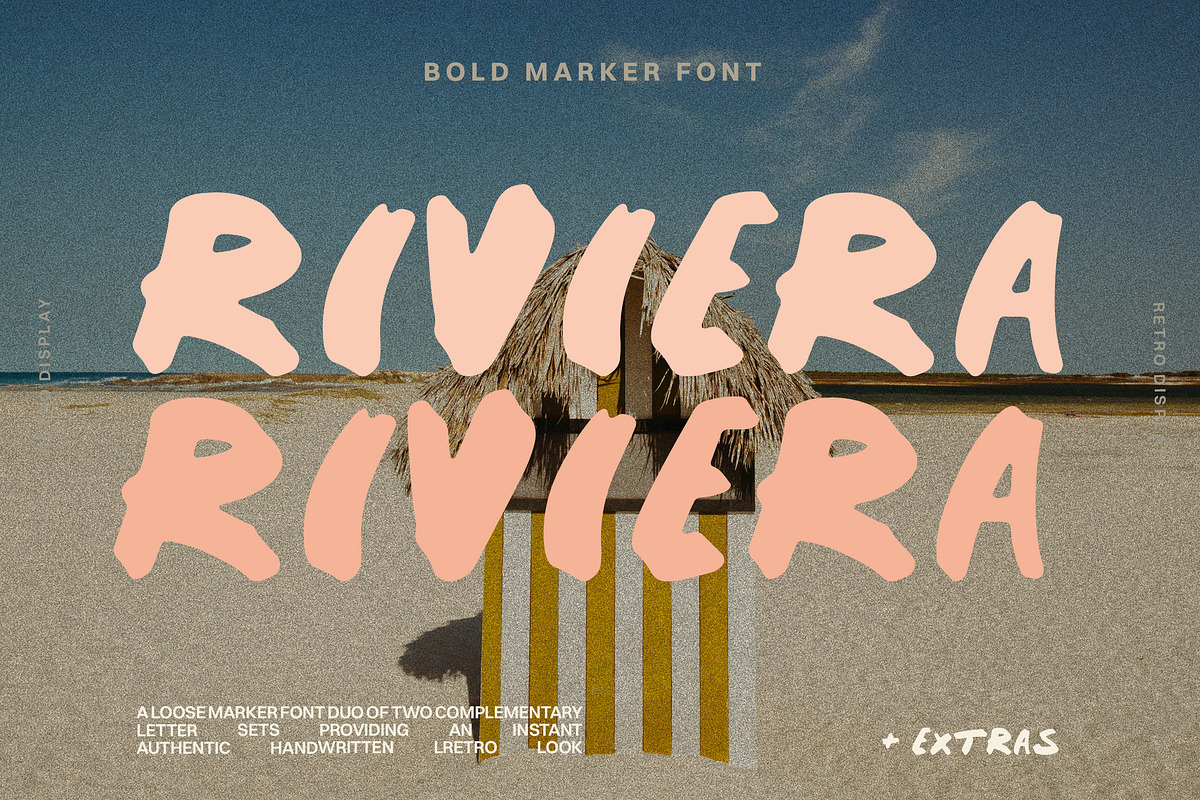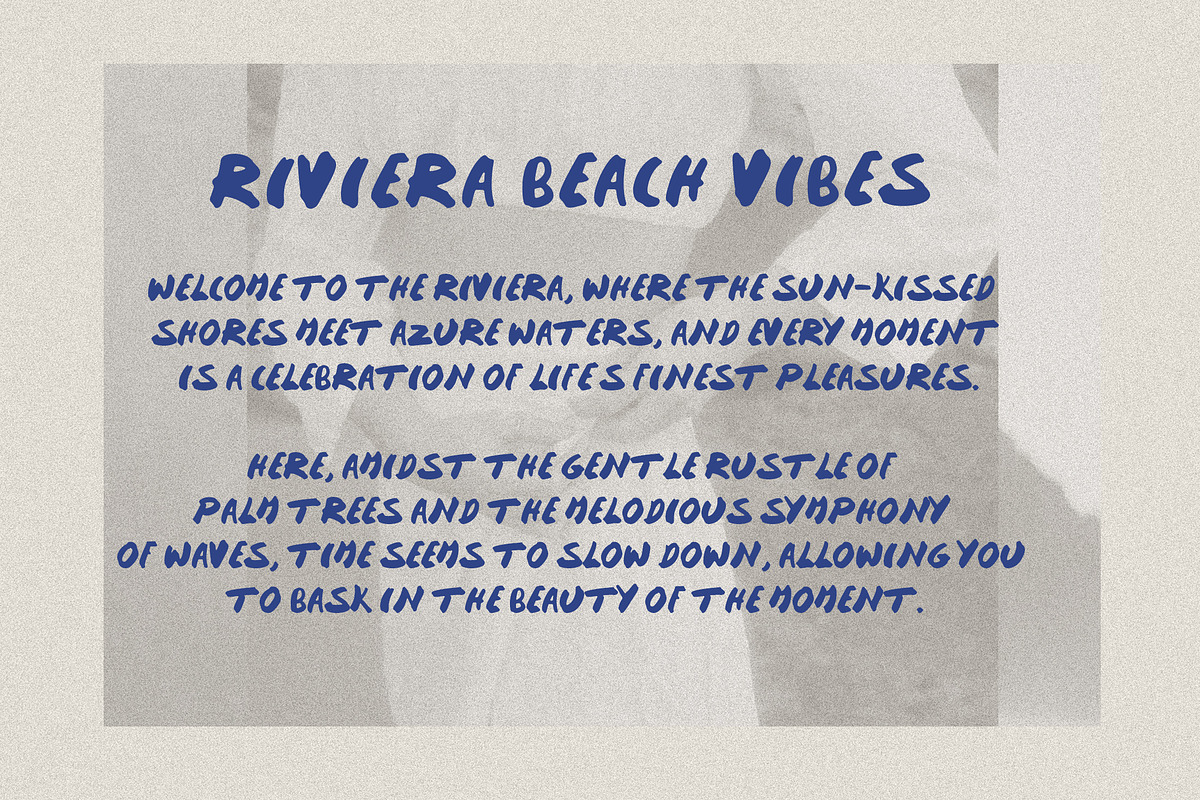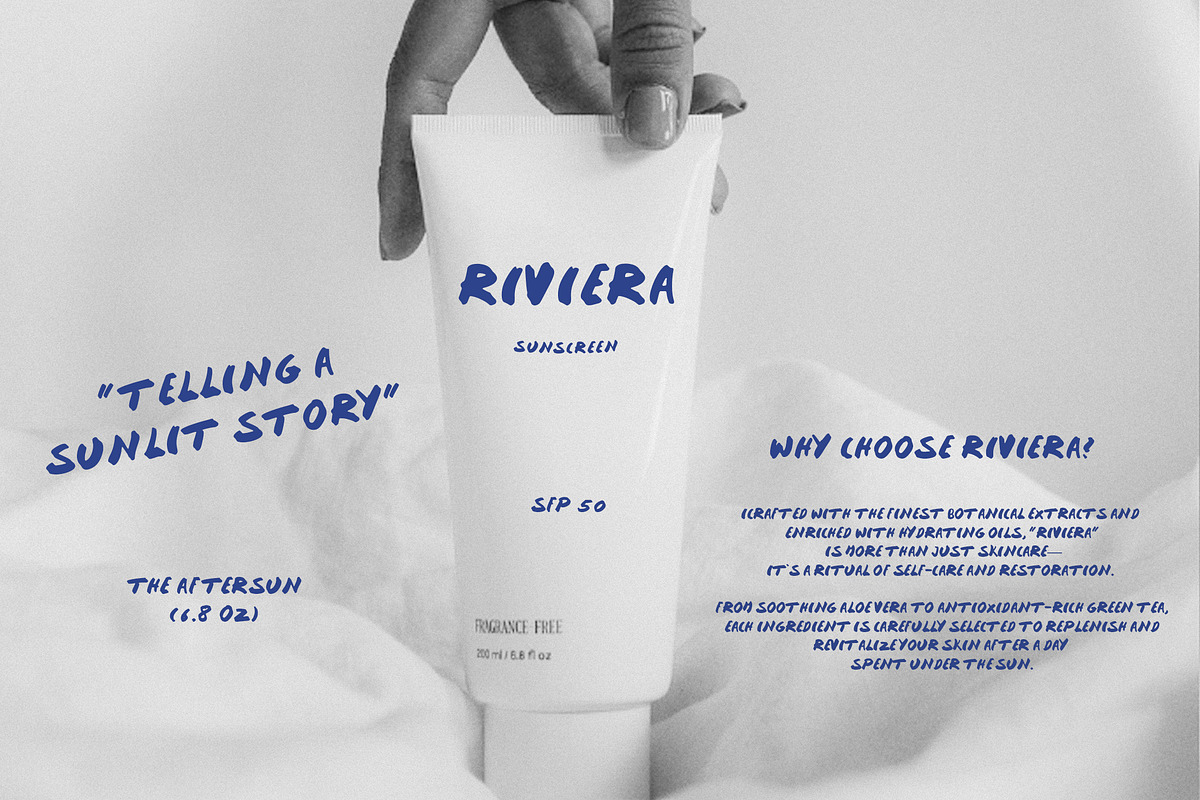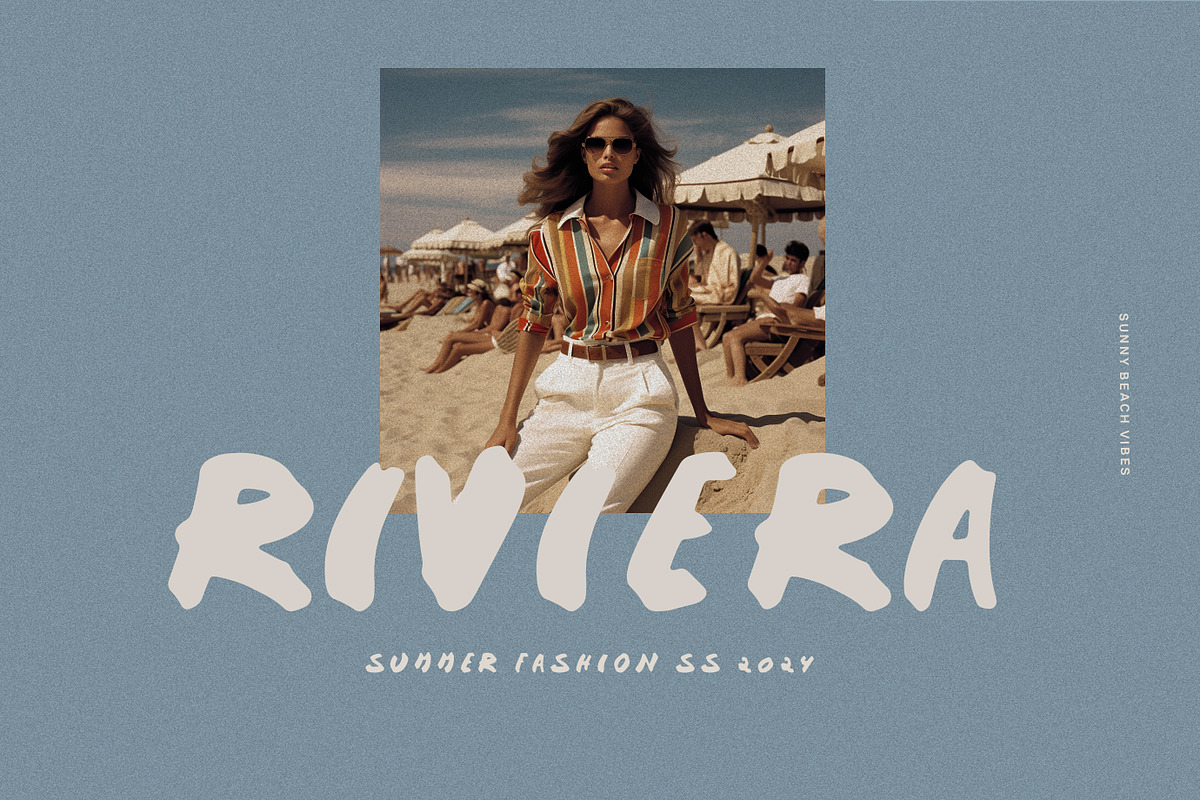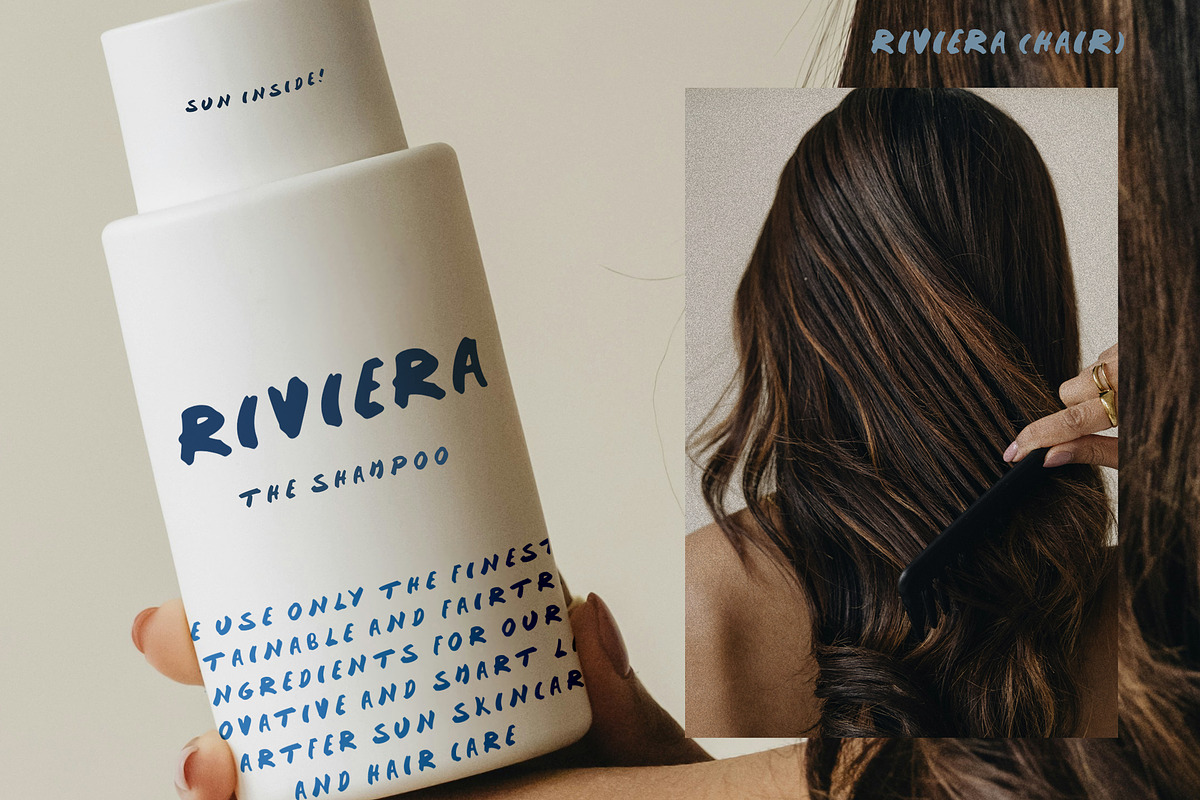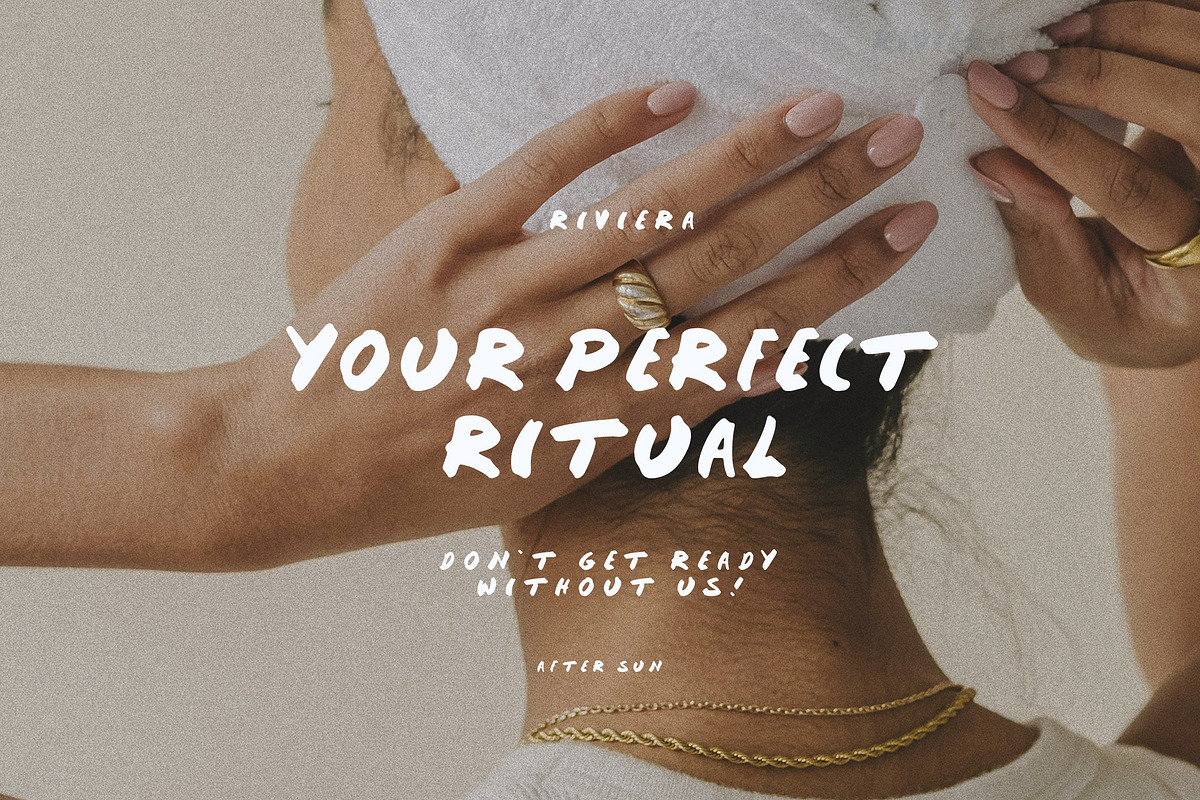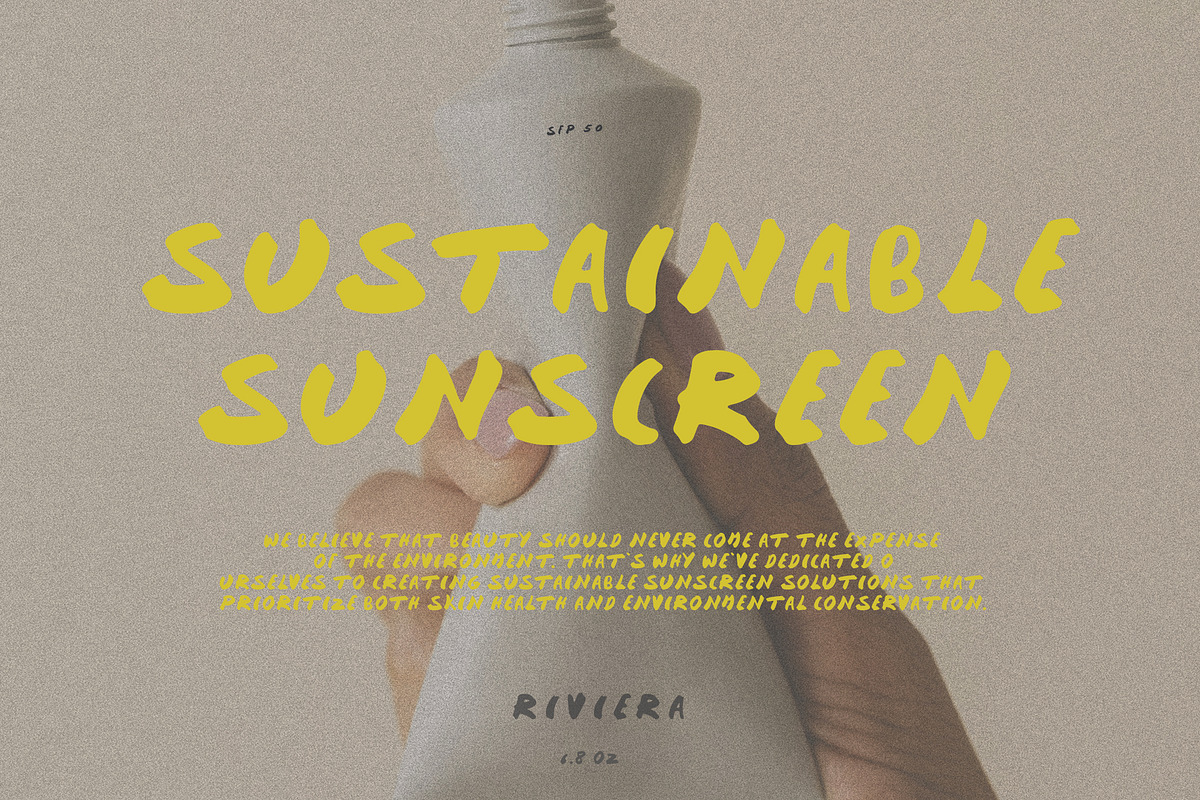
Bold Handwritten Marker Font
Riviera – Font Tulisan Tangan Modern dengan Sentuhan Ceria & Ilustrasi Unik
Riviera adalah font bergaya tulisan tangan yang menyenangkan, manis, dan modern secara alami. Dengan tampilan yang bold dan ujung goresan yang autentik, Riviera menjadi pilihan sempurna untuk desain kemasan, branding, logo, dan website. Nuansa catatan tangan yang dimilikinya juga sangat cocok untuk cetak poster, kutipan inspiratif, dan karya seni dekoratif lainnya.
Tak hanya font, Riviera juga hadir dengan berbagai ikon dan ilustrasi tambahan bertema pantai & seafood yang menggoda, menjadikannya paket lengkap untuk Anda yang ingin langsung mulai berkreasi!
Cocok digunakan untuk:
Logo, kemasan produk, undangan, website, sosial media, kutipan, dekorasi rumah, dan masih banyak lagi.